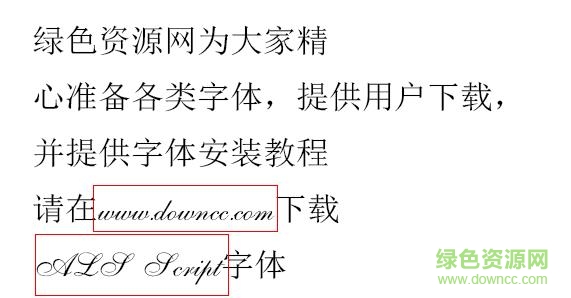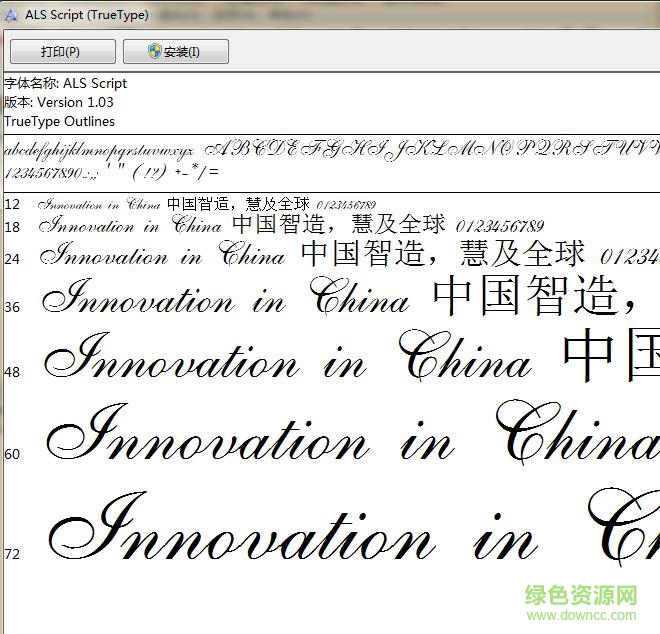
als script英文字體的樣式猶如中文狂草,讓你能夠感受到濃厚的水墨風(fēng)格,每一個(gè)字母與字母相連,同時(shí)又規(guī)律的扭曲樣式讓用戶眼前一亮,快來綠色資源網(wǎng)下載吧!
這款字體每一個(gè)字體都有一個(gè)彎曲的收尾樣式,帶給第一次使用的用戶一種視覺的美感,這樣的字體在英文字體的書寫過程中能夠更加的美觀!